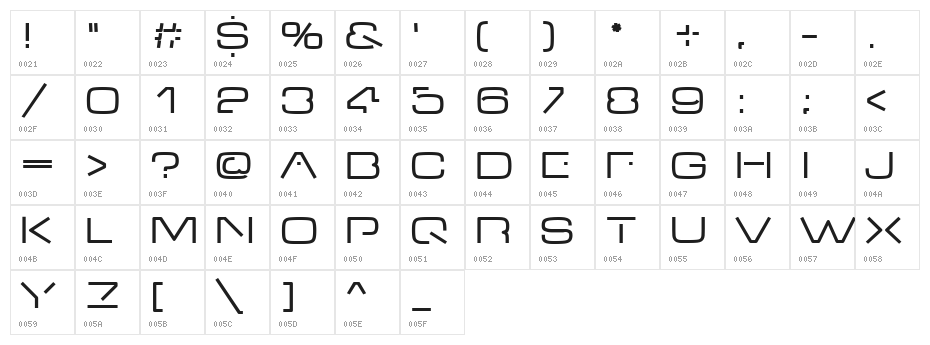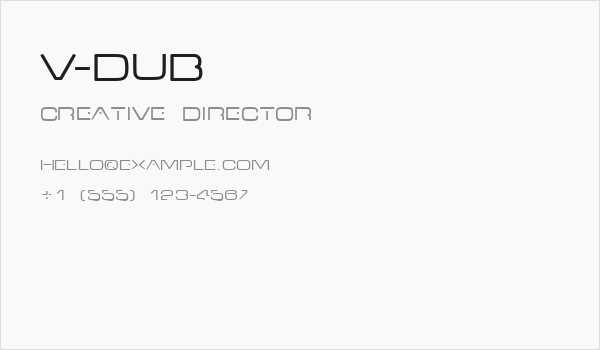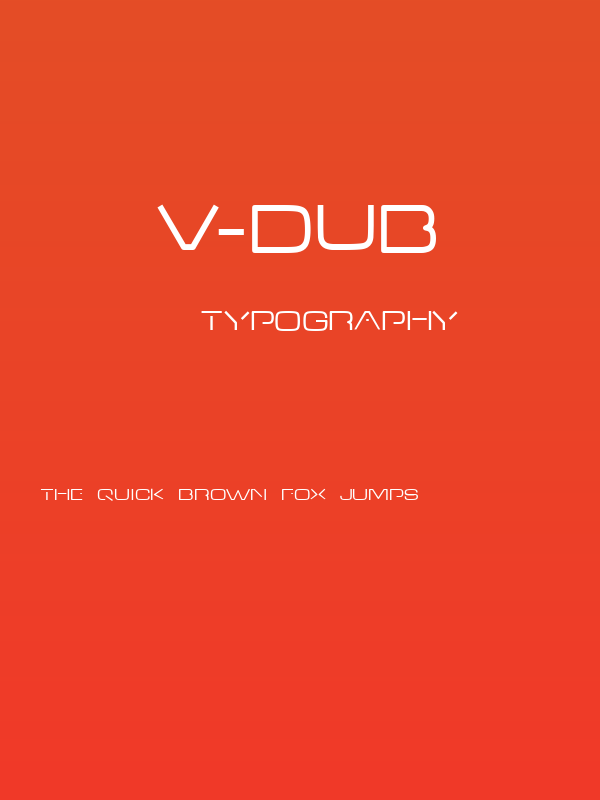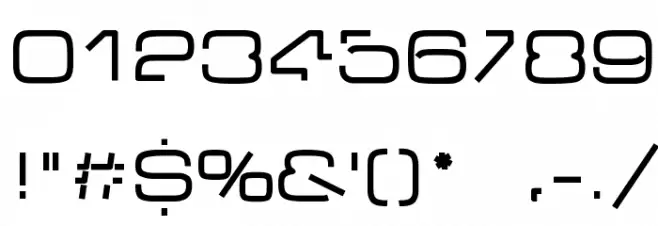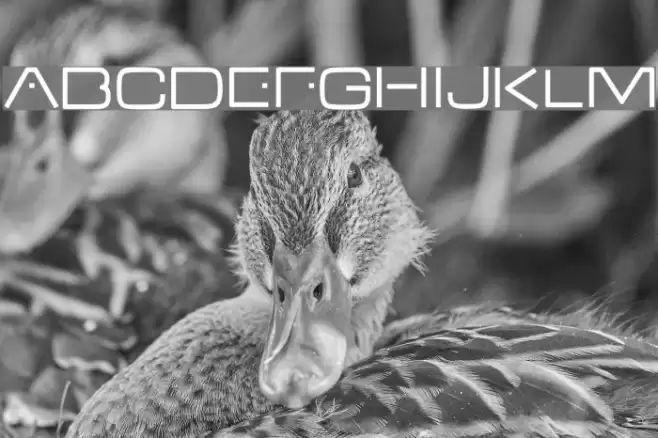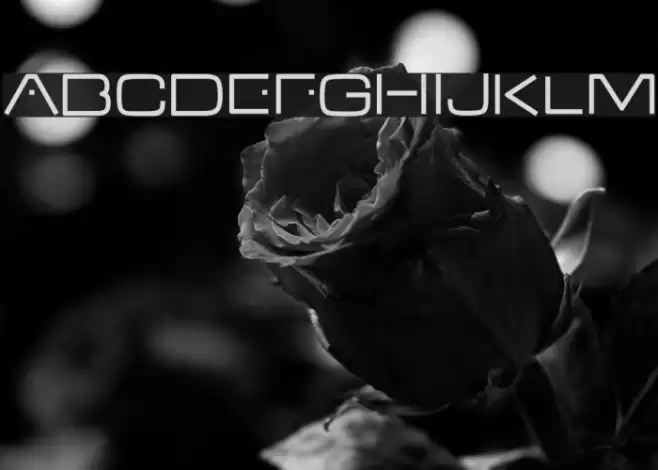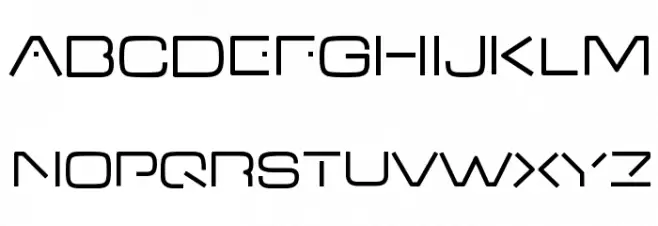
V-Dub Font
| Gesamtstil | Futuristic |
| Anwendungsfall | Logos, Headlines, Branding |
| Vorgeschlagene Projekte | Ideal for technology branding, sci-fi themed projects, modern advertising, and innovative product packaging. |